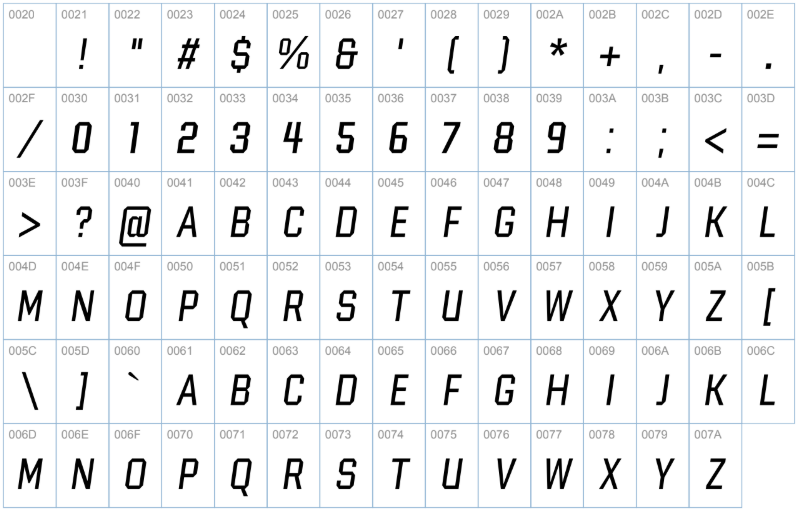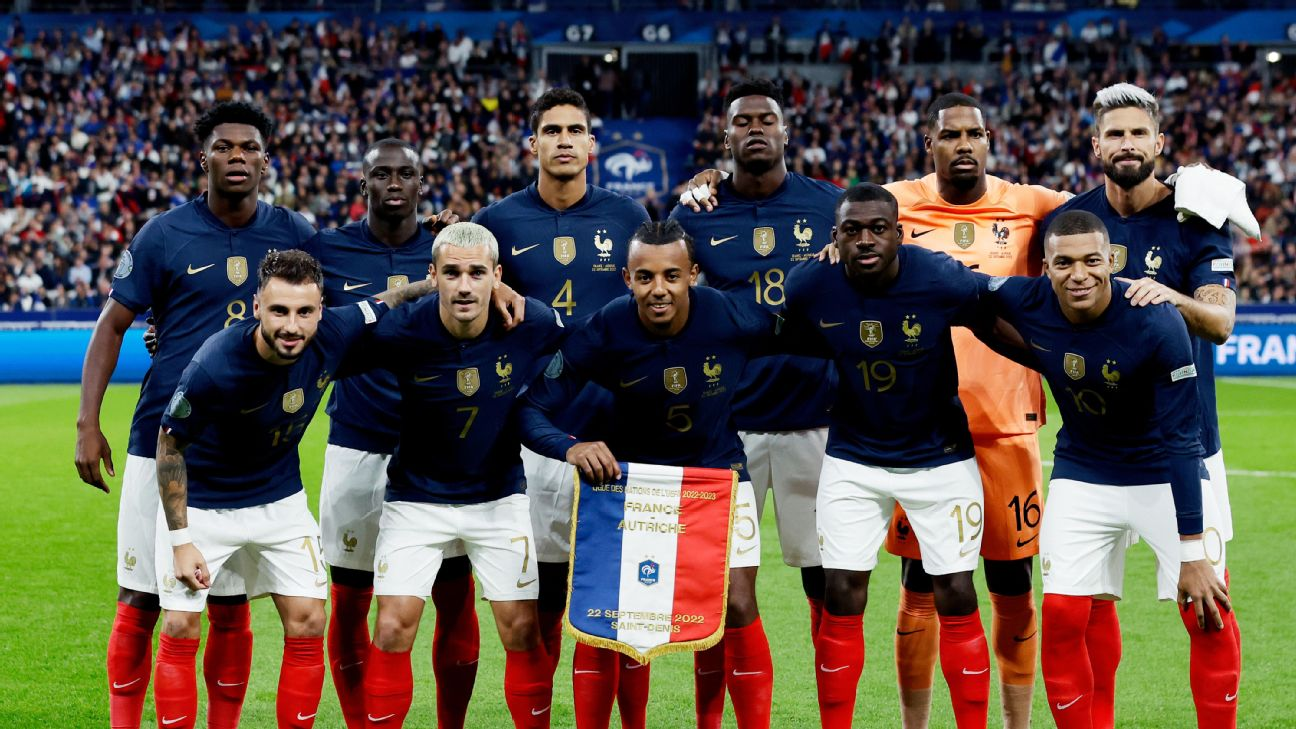
A Seleção Francesa entra em 2026 com os olhos no mundo e a identidade visual totalmente renovada. Para a temporada que promete ser histórica, cada detalhe importa — e a tipografia oficial é o elemento que fecha o uniforme com elegância e atitude.
Se você é fã dos Bleus ou designer em busca do arquivo perfeito, a fonte França 2026 chega com força. O lettering exclusivo traduz tradição e modernidade, pensado para brilhar tanto no gramado quanto nos projetos digitais.
Estilo visual da tipografia
A nova fonte aposta em traços retos e bem definidos, com serifas quase imperceptíveis que garantem um ar sofisticado. Os números têm recortes modernos e a haste do “1” ganha a icônica pegada geométrica que remete ao estilo parisiense contemporâneo.
A legibilidade é impecável: mesmo nas transmissões em 4K ou na arquibancada, cada nome brilha com nitidez. O equilíbrio entre tradição e inovação fica evidente no “7” anguloso e no “4” aberto, feitos para velocidade.
Aplicação no uniforme
- Home (Titular): Tipografia em branco sobre o azul-marinho, com acabamento vinílico premium.
- Away (Reserva): Versão em azul royal sobre base branca, trazendo forte contraste visual.
- Third (Terceira): Detalhes em dourado sobre vermelho, homenageando as raízes da FFF com toque de glamour.